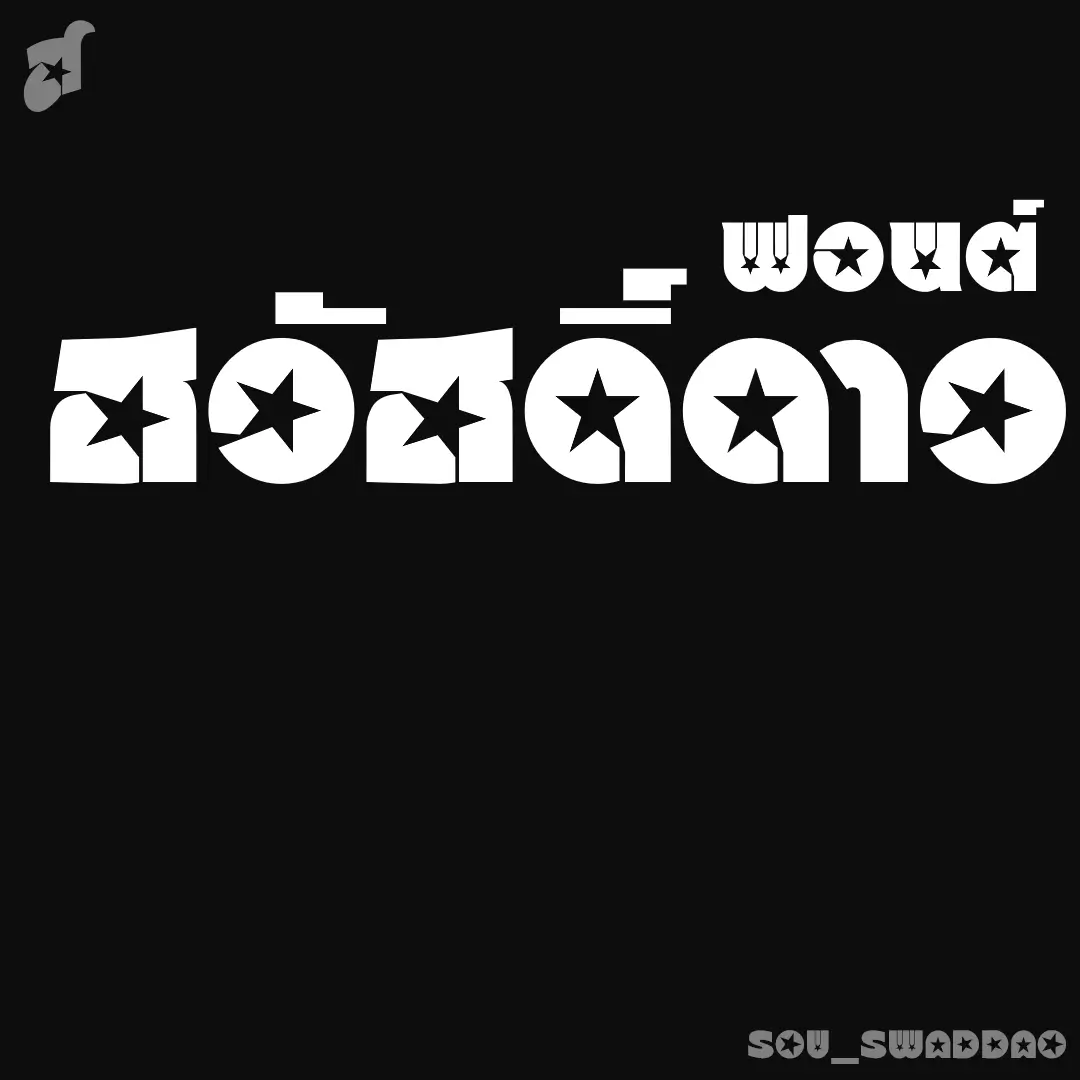
สวัสดิ์ดาว (SOV_SwadDao)
ฟอนต์สวัสดิ์ดาว – ต้นทางจาก หนังเรื่อง เทพธิดาท่าเรือ (Cinderella Liberty 1973) เป็นฟอนต์ตกแต่ง… ถ้ารู้สึกว่าเยอะไป ให้ใช้ผสมกับฟอนต์สวัสดี
เบื้องหลังการออกแบบ : ฟอนต์ สวัสดิ์ดาว